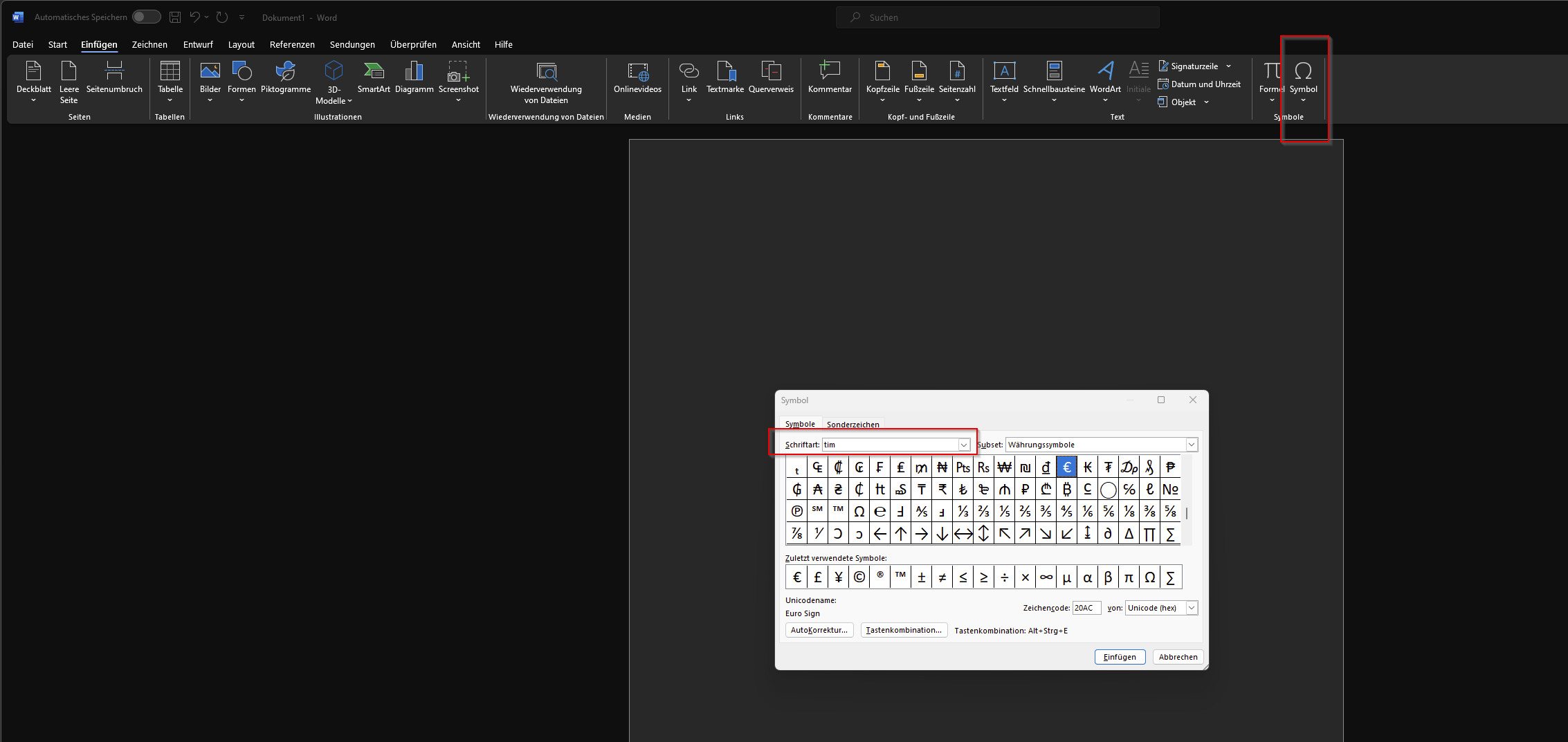
Hallo, ich bearbeite für die Uni ein Paper, das unter anderem einiges an Formeln erhält. Damit ich mit denen entsprechend arbeiten und sie in meine schriftliche Ausarbeitung miteinbeziehen kann, muss ich die Formeln aus der PDF irgendwie in mein Word dokument bekommen. Und das eben als Text und nicht einfach die Formeln screenshotten und dann das Bild ins Word Dokument einfügen😀
Dafür hab ich jetzt die Webanwendung Mathpix gefunden. Da lädt man seine PDF hoch und bekommt den Text inklusive Formeln in ein Word-Dokument konvertiert. Nun hab ich eine Frage dazu. Ausgespuckt wird beispielsweise sowas:
Das ist in der Schriftart "Cambria Math". Ich kenn mich in Word jetzt nicht sonderlich gut aus, aber Cambria Math ist die übliche Schriftart für Formeln oder? Kann man die noch irgendwie abändern? Von der Uni hab ich eine Formatvorlage bekommen, Schriftart ist dort Times New Roman. Kann man Formeln auch in Times New Roman anzeigen lassen? Wenn ich die Formel auswähle und die Schriftart ändere tut sich nichts 😥